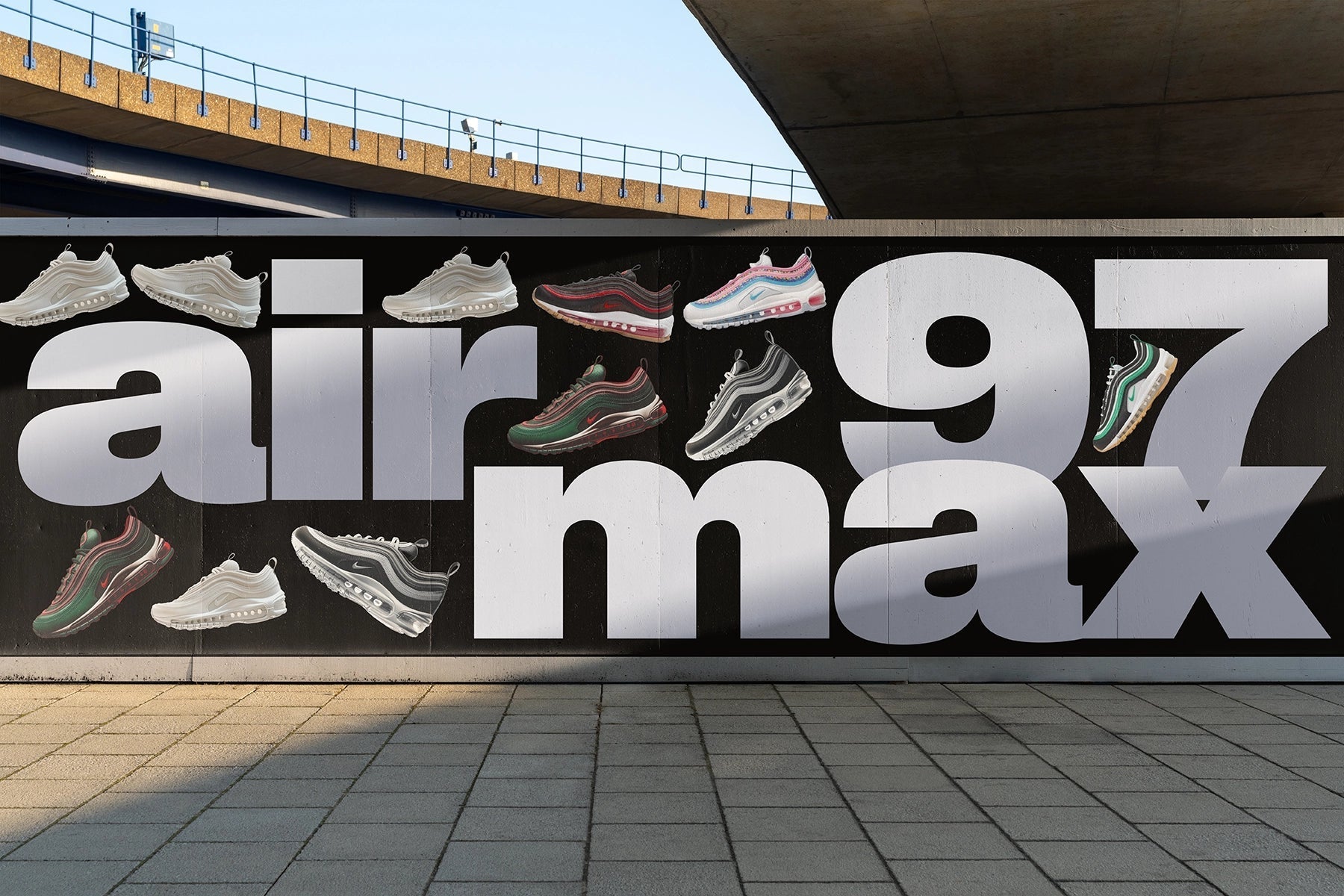
Helvetica demeure l'une des polices de caractères les plus influentes jamais conçues. Depuis sa création en 1957, elle a façonné le langage visuel de l'identité visuelle des entreprises, de la signalétique, des systèmes éditoriaux et des interfaces numériques.
Sa neutralité, sa cohérence et sa logique modulaire en ont fait le choix par défaut des designers qui souhaitaient que la typographie disparaisse derrière le contenu.
Mais cette neutralité même est devenue une limite. Helvetica est omniprésente. Elle évoque la sécurité, la conformité et un design institutionnel. Pour les designers contemporains, notamment ceux qui créent des marques, des interfaces et des systèmes éditoriaux dans un paysage visuel saturé, Helvetica paraît souvent surutilisée ou dénuée d'émotion.
La bonne nouvelle, c'est que la dernière décennie a vu naître une nouvelle génération de polices grotesques et néo-grotesques qui conservent la clarté fonctionnelle d'Helvetica tout en offrant davantage de texture, de chaleur et de personnalité. Chez Pangram Pangram, nous proposons plusieurs familles de polices qui se sont imposées comme d'excellentes alternatives, résolument modernes sans pour autant renoncer à la rigueur typographique.
Cet article explore cinq des meilleures alternatives à Helvetica issues de la bibliothèque Pangram et explique les points forts de chacune.
PP Nouveau Montréal
PP Neue Montréal est souvent le premier choix des designers qui recherchent une alternative directe mais subtilement plus expressive à l'Helvetica. Elle s'inscrit pleinement dans la tradition néo-grotesque tout en proposant des proportions plus contemporaines et plus humaines.
Là où Helvetica peut paraître rigide, Neue Montreal se distingue par sa fluidité. Ses courbes affirmées offrent un rendu naturel. Il en résulte une police de caractères particulièrement performante pour les identités visuelles, la mise en page éditoriale et les interfaces numériques. Elle a démontré au fil des ans toute sa force et sa polyvalence, s'imposant comme notre police la plus populaire. Découvrez des exemples d'utilisation remarquables dans notre section « Polices en usage » .
Neue Montreal est particulièrement adaptée aux projets qui requièrent neutralité et prise de position. Discrète, elle évite néanmoins l'anonymat d'Helvetica. Pour les designers travaillant sur des marques culturelles, des entreprises technologiques ou des projets de mode, elle offre une familiarité rassurante sans fatigue visuelle.
Neue Montréal excelle dans la rédaction de textes courants, de systèmes de navigation et de contenus longs où la clarté et le rythme sont essentiels.
PP Mori
PP Mori pousse l'idée d'une alternative à Helvetica vers une direction plus expressive. Tout en conservant une logique grotesque, Mori est une police sans serif gothique polyvalente et sophistiquée, inspirée du design japonais contemporain.
Cela rend PP Mori idéal pour les marques qui souhaitent projeter une image à la fois intelligente et contemporaine, sans pour autant se démarquer des entreprises traditionnelles. Cette police fait le lien entre modernisme rationnel et sensibilité organique. Elle dégage une impression de réflexion plutôt que de neutralité.
Mori excelle dans les contextes éditoriaux, l'identité de marque et les portfolios créatifs. Elle apporte une touche personnelle sans être décorative. Les graphistes qui trouvent Helvetica trop froide se tournent souvent vers Mori car elle conserve une excellente lisibilité tout en exprimant une personnalité unique.
Dans les produits numériques, Mori peut humaniser les interfaces, notamment sur les plateformes riches en contenu où le ton compte autant que la facilité d'utilisation.
PP Neue Corp
PP Neue Corp est une alternative à Helvetica, plus incisive. Inspirée des caractères industriels et d'entreprise, elle privilégie la structure, la densité et l'autorité. C'est donc un excellent choix pour les designers qui recherchent la précision et la force plutôt que la douceur.
Neue Corp convient parfaitement aux identités qui doivent communiquer sérieux, expertise ou crédibilité technique. Les marques des secteurs de la finance, de l'architecture, de la recherche et des infrastructures bénéficient de son ton rigoureux.
Comparée à Helvetica, Neue Corp se distingue par une personnalité plus affirmée et un caractère moins générique. Ses proportions sont plus resserrées, ses détails plus marqués. Il en résulte une maîtrise et une clarté qui font parfois défaut à Helvetica dans un contexte contemporain. Neue Corp est une police polyvalente, conçue avec une large gamme de largeurs et de graisses. Elle permet aux designers et aux studios de l'adapter à tous les contextes, des titres percutants aux textes courants épurés. Alliant caractère et neutralité, elle combine l'excentricité des caractères en bois anciens à la précision des néo-grotesques.
Pour les systèmes de marque à grande échelle, la signalétique et les titres percutants, Neue Corp offre confiance et options.
PP Droite Grotesk
Alliant la neutralité et la polyvalence des polices classiques à une personnalité subtile mais affirmée, Right Grotesk est la police idéale pour allier structure et âme. Elle dégage une assurance tranquille, capable de mettre en valeur un titre ou un texte en petits caractères. Son design équilibre une logique utilitaire avec quelques touches d'originalité. Des courbes douces. Un contraste modéré. Une anatomie inattendue mais élégante qui apporte une touche de fraîcheur sans tomber dans le gadget.
PP Neue Montréal est la plus proche en termes d'esprit, offrant une familiarité raffinée. PP Mori apporte chaleur et émotion. PP Neue Corp met l'accent sur l'autorité et la structure. PP Right Grotesk offre une expression audacieuse. PP Radio Grotesk ajoute une dimension historique et narrative.
Le choix de la meilleure solution dépend du ton recherché pour votre projet. En pratique, la typographie n'est jamais neutre, elle est toujours contextuelle.